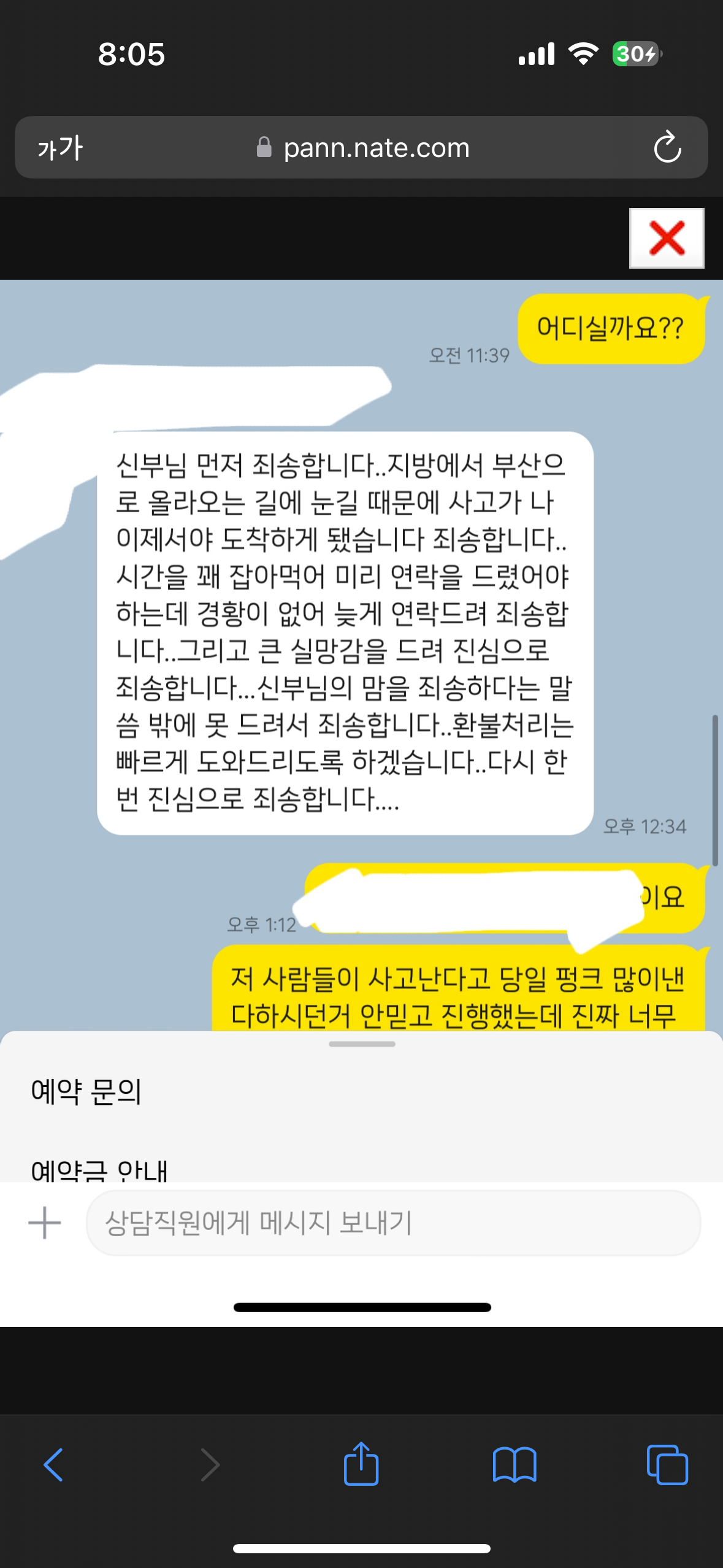
폰트 궁금해요ㅠㅠ sos*** 2023.10.05 고딕에 가까운데 무슨 폰트인지 아시는분 계신가요ㅠㅠ 댓글 0 등록 rht*** 나눔스퀘어 네오 폰트 같아요! 2023-10-08 답글 달기 sta*** Aa합정산스 같네요 https://blog.naver.com/aafont/221489420600 2023-10-06 답글 달기 댓글 더보기 쉽고 빠르게 가장 비슷한 폰트를 알고 싶다면? 이미지로 검색하기
나눔스퀘어 네오 폰트 같아요!
Aa합정산스 같네요 https://blog.naver.com/aafont/221489420600